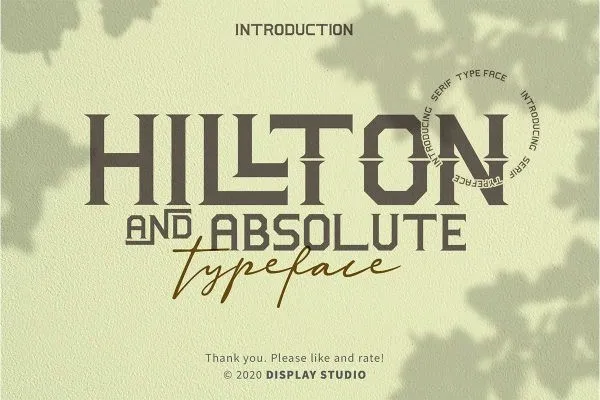
Hillton and Absolute Font – Download Grátis
Esta é uma fonte ‘Hillton and Absolute’ que traz à vida elementos vintage e elegantes, característicos do estilo Victoriano. Ideal para logos de marcas, cartões de convite, encomendas ou até mesmo projetos de qualquer tipo, essa fonte se destaca por sua versatilidade multilíngue e variedade de estilos únicos que adicionarão um toque elegante aos seus trabalhos. Com suas linhas arredondadas e traços curvados, Hillton and Absolute oferece uma experiência visual única e atrativa. Suas formas arquitetônicas e a elegância dos tempos modernos da década de 1800 são expressivas em cada letra, criando um conjunto perfeito para qualquer uso. Seja você designer gráfico, ilustrador ou editor de fotos, esse é o tipo de fonte que adicionará sofisticação e um toque inconfundível ao seu trabalho. Através de sua linguagem multilíngue, a fonte Hillton and Absolute permite uma ampla gama de aplicabilidades em diferentes idiomas. Este tipo especializado não apenas ressalta o texto, mas também torna cada projeto mais memorável e personalizado, criando um impacto visual imediato e marcante. Com sua versatilidade de estilos únicos e características vintage inovadoras, Hillton and Absolute é uma fonte que enriquecerá a beleza das suas criações. Se você busca uma fonte única para dar vida ao seu próximo trabalho, vale a pena considerar essa elegância arquitetônica em sua paleta de ferramentas digitais.